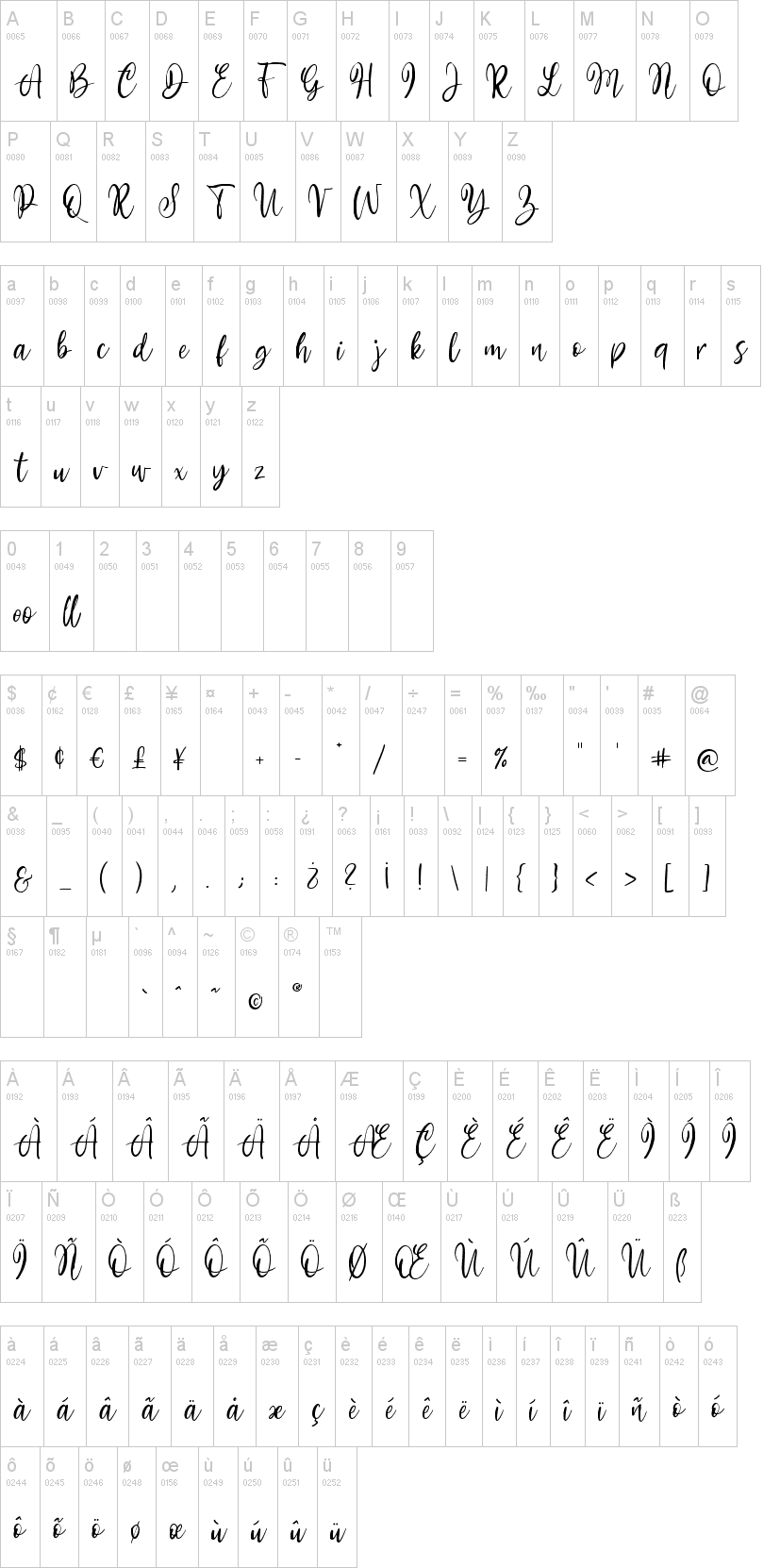
Mollywood
Mollywood字体是一款结合了韩国文字特点的字体,它结合了韩国文字的细节,让文字看起来更加精致,更有趣。Mollywood字体的字体细节更加精致,更有趣,它的字形也更加简单,更加容易阅读,它的字体也更加圆润,更加柔和,所以它适用于各种类型的设计,比如海报、书籍封面、标志等等。
Mollywood是一款非常不错的手写艺术字体,具有很好的视觉感,适合于文化类的宣传设计、商业类品牌的广告和产品包装设计以及个性化文字排版等较多场景。
Mollywood字符映射图